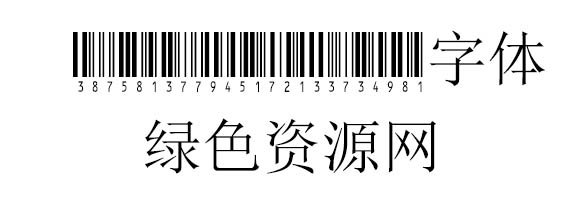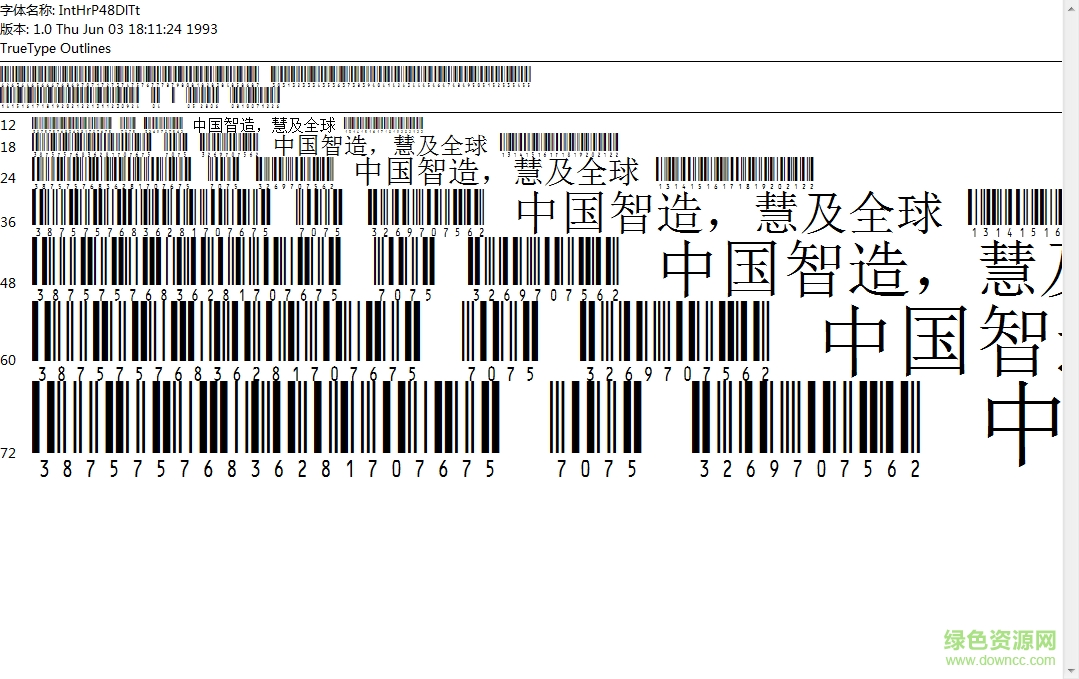
IntHrP48DlTt條碼字體是一款為需要條形碼字體的用戶打造的IntHrP48DlTt字體,此款字體樣式非常好看,適用于各種產(chǎn)品包裝,需要的朋友來綠色資源網(wǎng)下載!
IntHrP48DlTt條碼字體是非常好用的條形碼字體,它與其他條形碼不同的是在它的下面還會(huì)帶有不同的數(shù)字呈現(xiàn)